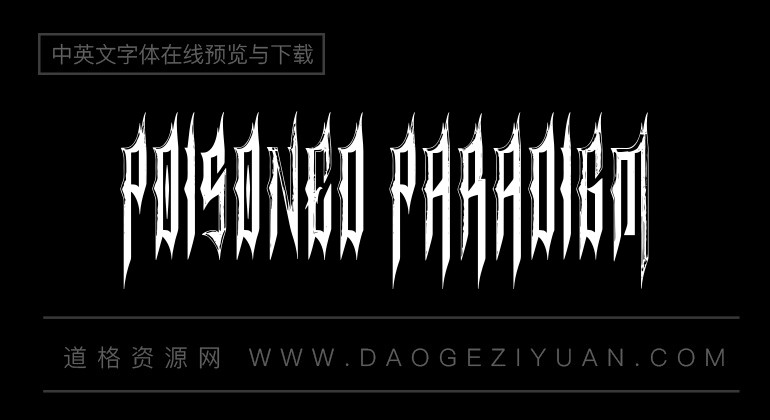
? Poisoned Paradigm是一款拥有明快、有力、活力的复古字体,它具有极具现代感的设计,适合用于标题、标签、标识、标志等等。它具有极大的弹性,可以调节字体的大小,以满足不同的设计需求。它的构图、字形、字距以及字体的细节都更加精细,更加精致,更加令人印象深刻。内容介绍
Poisoned Paradigm是一款非常不错的手写艺术字体,具有很好的视觉感,适合于文化类的宣传设计、商业类品牌的广告和产品包装设计以及个性化文字排版等较多场景。